「CGプロダクション年鑑 2018」にてフォントワークス「LETS」紹介記事が掲載
2018年の「CGプロダクション年鑑」ではフォントワークスの定額制フォントサービス「LETS」の紹介記事が掲載されている。
「LETS」使用事例「八月のシンデレラナイン」
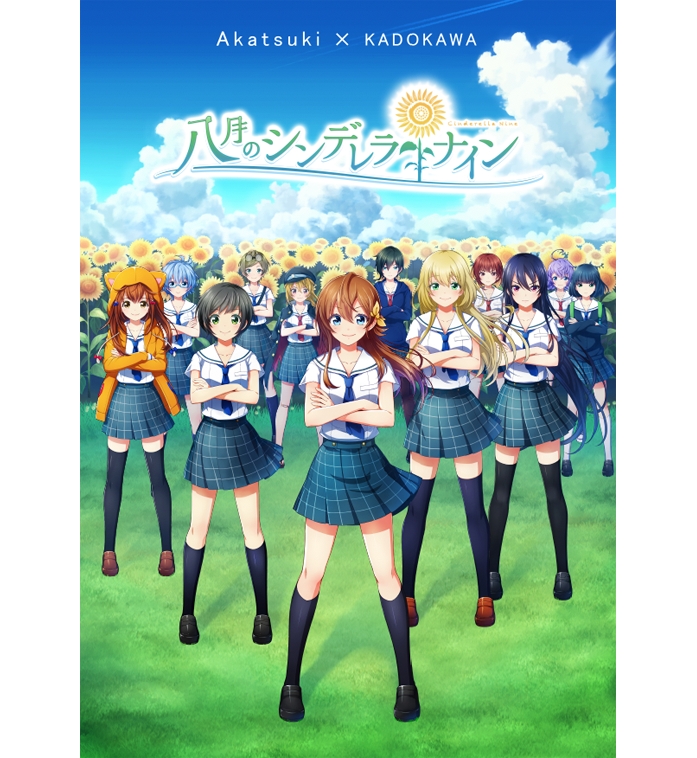
記事内ではフォントワークス「LETS」の使用事例としてアカツキのスマートフォンゲーム「八月のシンデレラナイン」での使用フォントが紹介されている。
「八月のシンデレラナイン」のタイトルロゴの使用フォントは筑紫オールド明朝。
選定理由は、八月のシンデレラナインのテーマである青春を再現するために、芯(安定感)はあるが美しい曲線をもち、伸びのあるラインが出せること。自社IPブランドロゴとして単色でも洗練されたデザインであり、その意図には、まっすぐ部活に向き合うイメージができるように、直線と組み合わせても本来の伸びやラインの美しさを損なわないフォントとのこと。
筑紫オールド明朝はフォントワークスを代表する「筑紫書体」のオールドスタイルの明朝体。美しい打ち込みや伸びやかなハネ、ハライが特徴。
また、選手詳細紹介の使用フォントには「スキップ」が採用されている。
こちらの選定理由は、ゲーム内のダイナミックフォントとして使用。単語ではなく文章として可読性が高く、小さく表示しても読み疲れないことで、その意図には誠実な印象を与え、適度な崩しがあり、ポップさ、かわいさを兼ね備えたデザイン性のあるフォントと掲載されている。
スキップはまじめな印象を与えながらも適度なファッション性を加味した書体をスクエアタイプで表現した書体。
その他、イベント告知用バナーとして、京円かな太やマティスなども使用されている事が紹介されている。